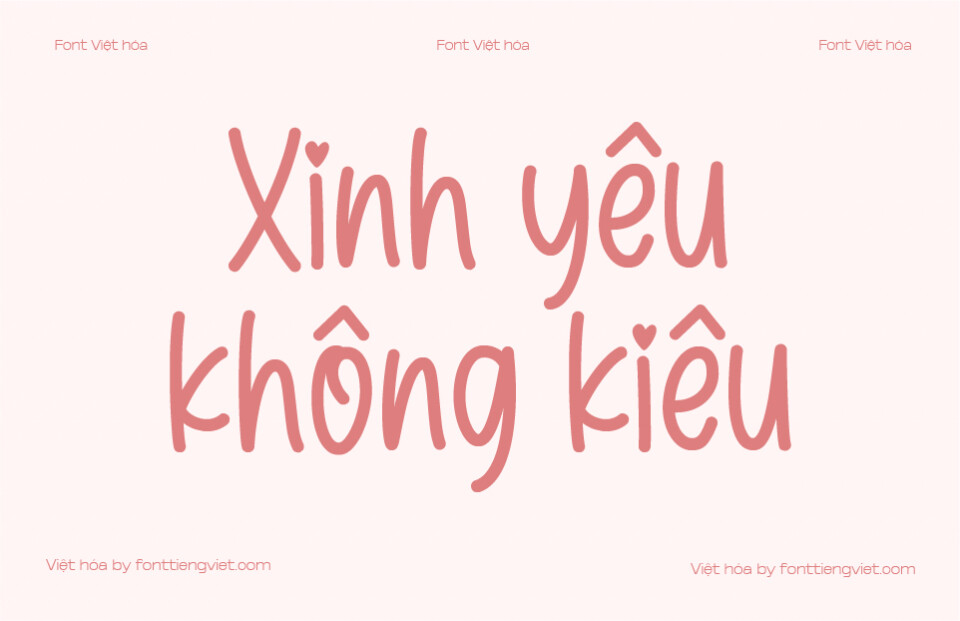
Trong thế giới thiết kế đồ họa và nội dung số, việc lựa chọn một Font Chữ phù hợp có ý nghĩa vô cùng quan trọng, đặc biệt đối với học sinh, sinh viên đang thực hiện các dự án học tập và đồ án tốt nghiệp. Bài viết này sẽ đi sâu vào một trong những lựa chọn hàng đầu hiện nay: Font Việt hóa 1FTV VIP Romantic. Đây không chỉ là một kiểu chữ đẹp mắt mà còn là công cụ giúp các dự án của bạn trở nên chuyên nghiệp, thu hút và mang đậm tính nghệ thuật lãng mạn. Chúng ta sẽ cùng khám phá những đặc điểm nổi bật và cách tối ưu hóa font này cho các mục đích SEO và sáng tạo.
Giới Thiệu Chi Tiết về Font Việt hóa 1FTV VIP Romantic
Font 1FTV VIP Romantic được biết đến là một kiểu chữ script, mô phỏng nét viết tay thanh lịch, mềm mại, thường được sử dụng trong các thiết kế đòi hỏi sự tinh tế và cảm xúc. Đặc điểm “VIP” của font này thường ám chỉ chất lượng cao cấp, độ nét hoàn hảo và bộ ký tự đầy đủ. Tuy nhiên, điều làm nên giá trị thực sự của font này tại Việt Nam chính là quá trình “Việt hóa”. Quá trình này đảm bảo rằng tất cả các ký tự đặc biệt, dấu câu, và đặc biệt là các dấu tiếng Việt (như ã, ơ, ư, đ) được hiển thị chính xác và mượt mà, tránh tình trạng lỗi font hay vỡ chữ thường gặp. Đối với học sinh cấp 3 chuẩn bị cho các hoạt động kỷ niệm, hay thiết kế thiệp mời dự lễ tốt nghiệp, sự mềm mại của Font Việt hóa 1FTV VIP Romantic mang lại cảm giác sang trọng và chuyên nghiệp tuyệt đối.
Phong Cách Lãng Mạn và Ứng Dụng Trong Học Đường
Phong cách lãng mạn (Romantic style) của font 1FTV VIP Romantic rất được ưa chuộng trong các dự án cá nhân của sinh viên. Nó phù hợp để tạo tiêu đề cho một bài thuyết trình sáng tạo, thiết kế bìa cho tập kỷ yếu, hoặc thậm chí là trang trí cho bảng tin trường học. Khi sử dụng font này, thông điệp truyền tải sẽ có chiều sâu cảm xúc hơn, giúp bài làm của bạn nổi bật giữa đám đông. Khả năng tương thích tốt với các phần mềm thiết kế phổ biến như Adobe Photoshop, Illustrator, và ngay cả Microsoft Word/PowerPoint là một lợi thế lớn cho người dùng không chuyên.
Tối Ưu Hóa Bài Luận Văn và Đồ Án Tốt Nghiệp
Đối với các dự án cuối cấp hay luận văn đại học, sự lựa chọn font chữ thường bị giới hạn bởi các quy tắc nghiêm ngặt (như Times New Roman hoặc Arial). Tuy nhiên, 1FTV VIP Romantic vẫn có thể được sử dụng một cách chiến lược. Chẳng hạn, bạn có thể dùng nó cho trang bìa phụ, các trích dẫn đặc biệt, hoặc các thiết kế minh họa đi kèm trong phụ lục. Điều này giúp cân bằng giữa sự trang trọng cần có và sự sáng tạo cá nhân. Nắm vững cách sử dụng các font script như thế này là một kỹ năng thiết kế đồ họa quan trọng mà học sinh, sinh viên hiện đại cần trau dồi.
Tóm lại, việc sở hữu và sử dụng hiệu quả Font Việt hóa 1FTV VIP Romantic là một lợi thế lớn cho bất kỳ ai hoạt động trong lĩnh vực sáng tạo, đặc biệt là các bạn học sinh đang chuẩn bị cho các dự án quan trọng. Font mang lại sự kết hợp hoàn hảo giữa nét cổ điển lãng mạn và tính hiện đại, được Việt hóa chuẩn mực. Đừng ngần ngại bổ sung kiểu Font Chữ độc đáo này vào bộ sưu tập của mình để nâng cao chất lượng thẩm mỹ cho mọi tài liệu, từ bài thuyết trình đơn giản đến các ấn phẩm liên quan đến kỳ thi tốt nghiệp quan trọng. Hãy tận dụng tối đa sức mạnh của typography để biến những ý tưởng của bạn thành hiện thực một cách ấn tượng nhất.